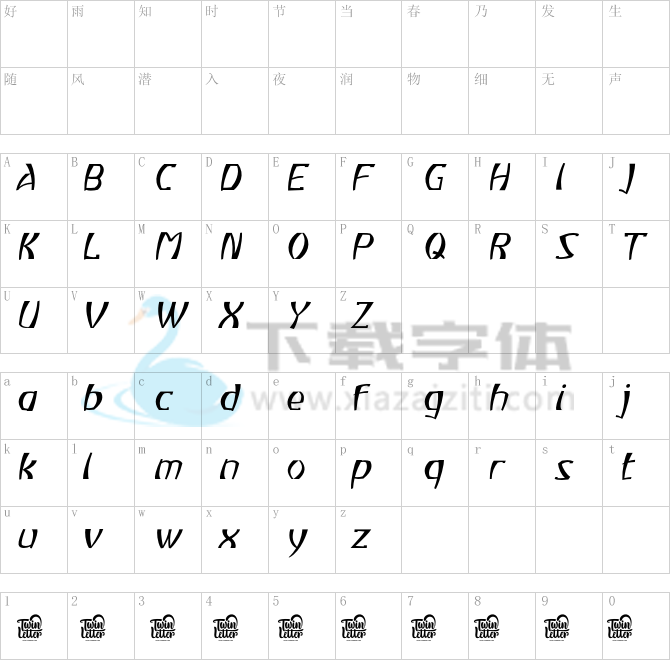
Atiku Thin Slant.otf字体下载,这款字体结构工整、笔画清晰,兼顾美观与易读性,适用于标题、正文、海报、包装、LOGO 等多种场景。字形优雅稳定,风格百搭耐看,适配日常排版与创意设计,让文字呈现更舒适、更具质感。Atiku Thin Slant.otf字体下载一笔一画,皆是细节,以均衡的比例、流畅的线条打造舒适视觉体验,字形端正大气,风格简约现代。无论是商业设计、品牌宣传还是日常排版,都能轻松驾驭,让文字更有格调与力量。Atiku Thin Slant.otf字体下载字体下载。